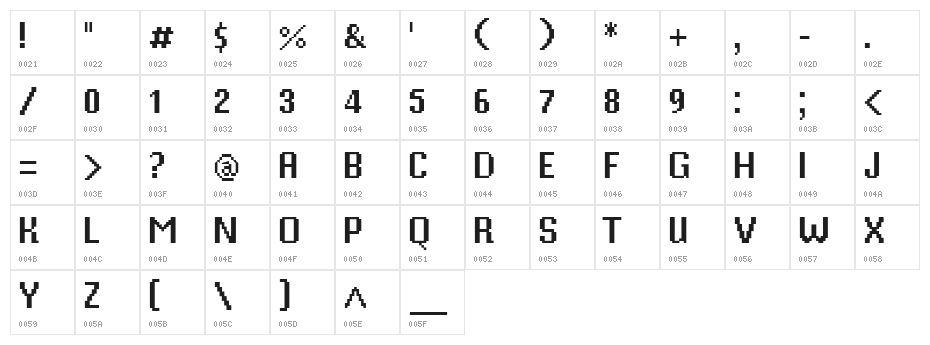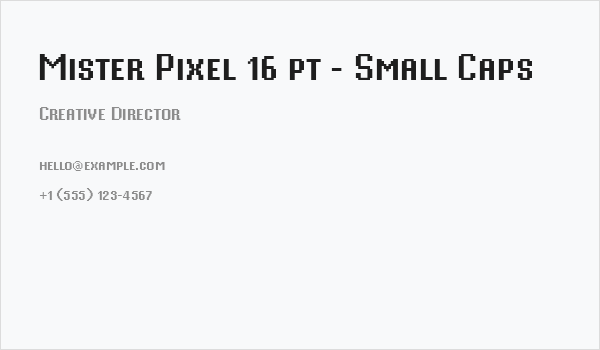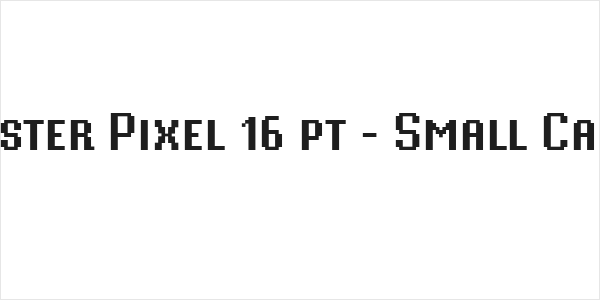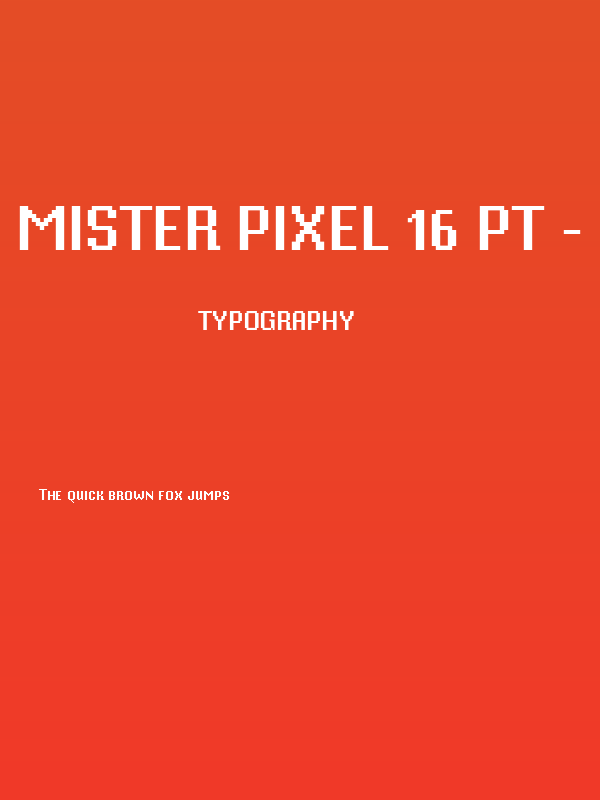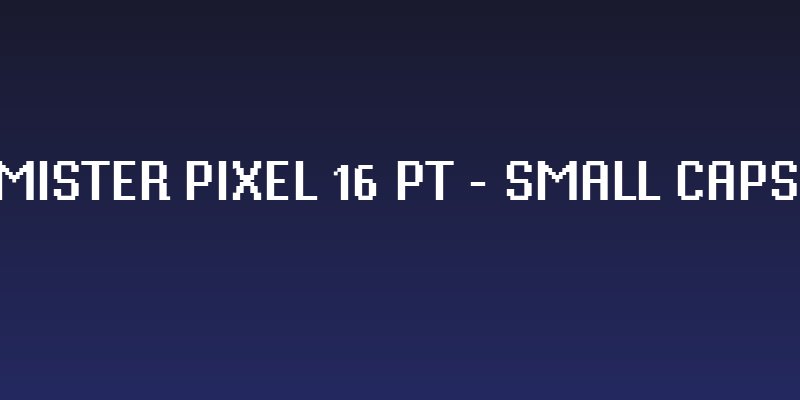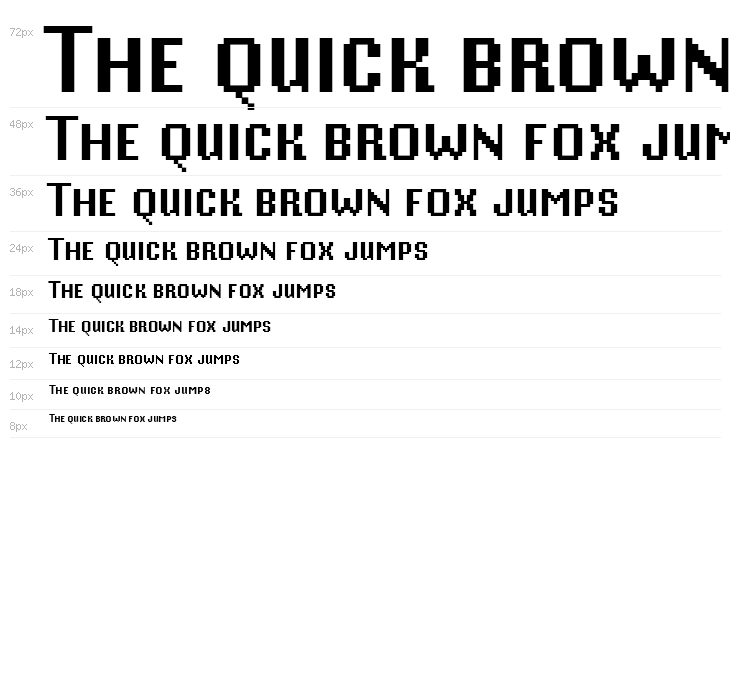
Mister Pixel 16 pt - Small Caps Font
| 分类 | Pixel |
| 整体风格 | Vintage |
| 使用场景 | Headlines, Logos, Digital Art |
| 推荐项目 | Ideal for projects that require a retro or digital theme, such as video game graphics, tech-themed posters, or nostalgic branding. |